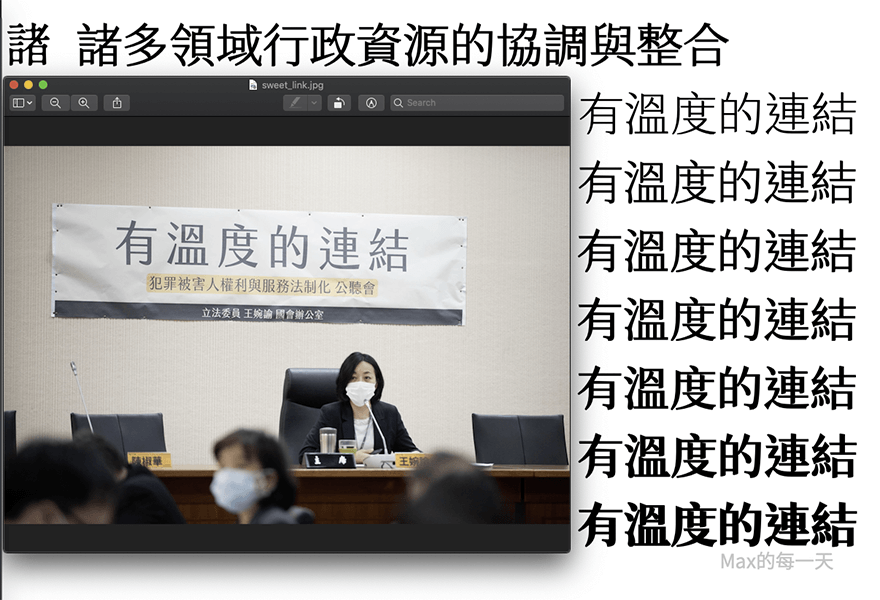
宋體
獅尾
Max前幾天看到一篇文章,在講有溫度的連結,然后看到橫幅上的字體,可能是金萱的字體,非常特別,這款字體把黑體和宋體結合了在一起,看上去非常好看。于是Max通過程序修改思源宋體,把思源宋體里的右邊三角形襯線拿掉,并幫字體取名為獅尾四季春。雖然不太完美,但是看上去感覺還不錯。
獅尾四季春是基于思源宋體拔三角形改造,看上去會更加簡明現代化,版面效果清新輕快。缺點是比較輕,橫筆明顯極細。和思源宋體一樣,獅尾四季春支持簡體中文、繁體中文、韓文與日文,并且支持6個字重。